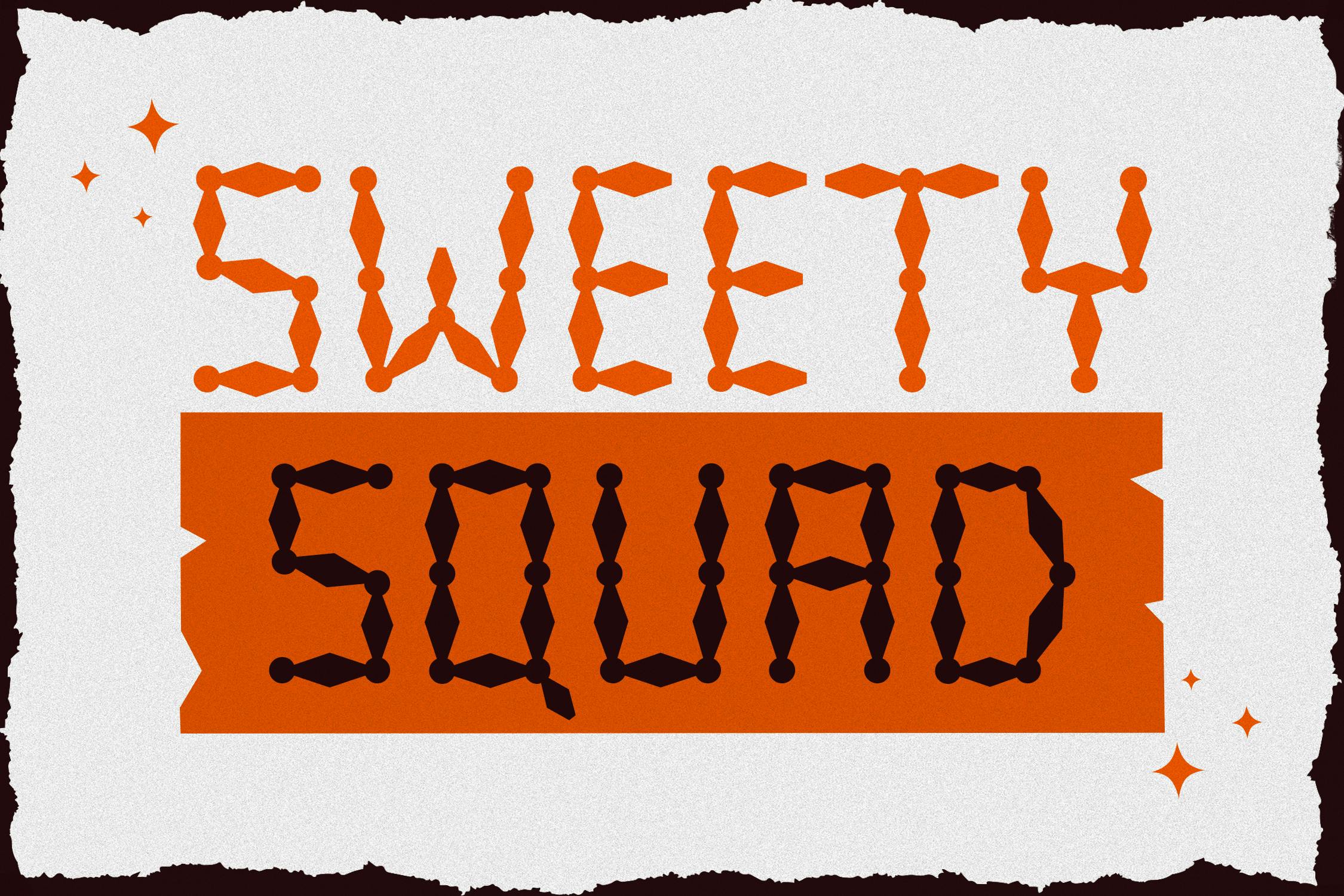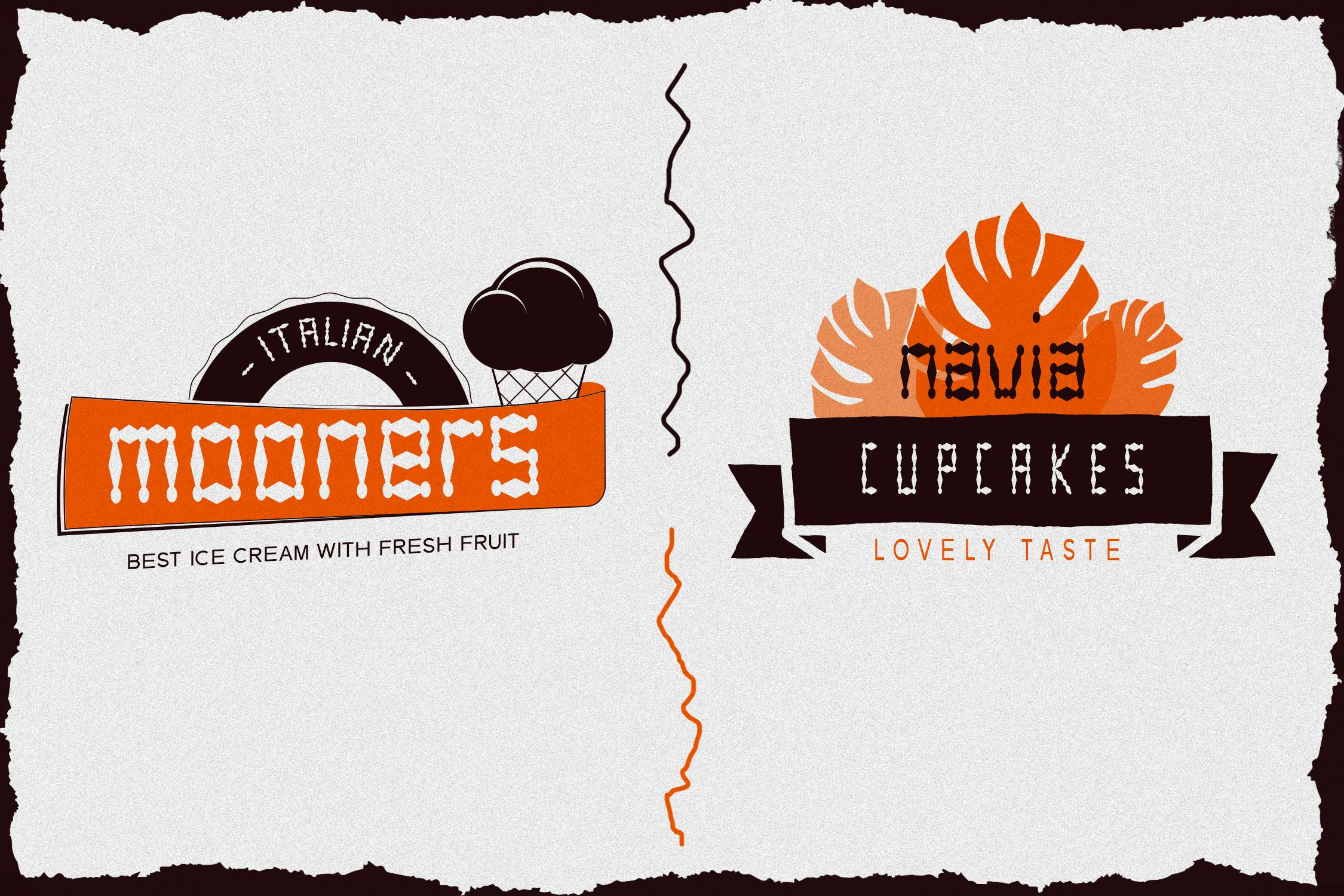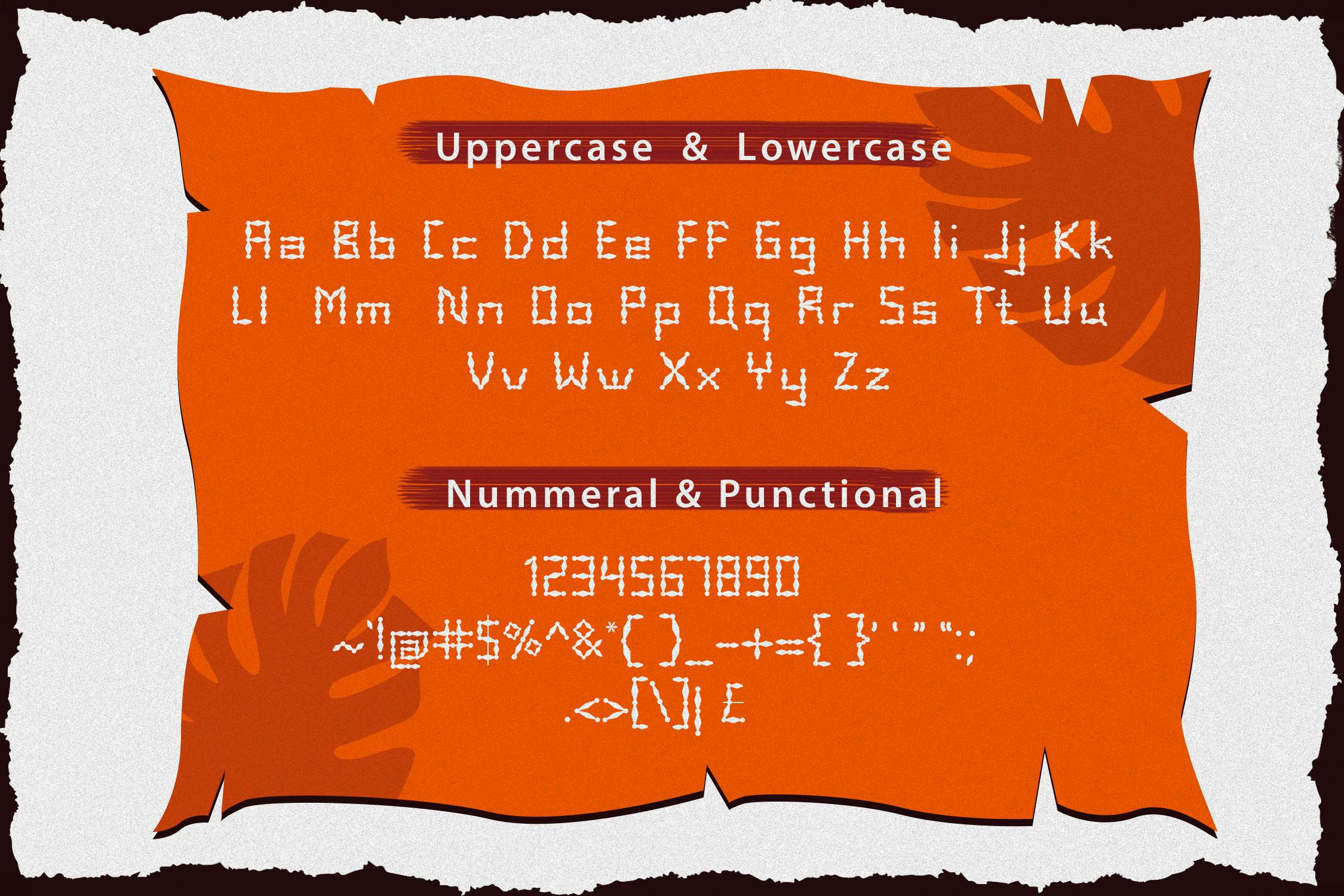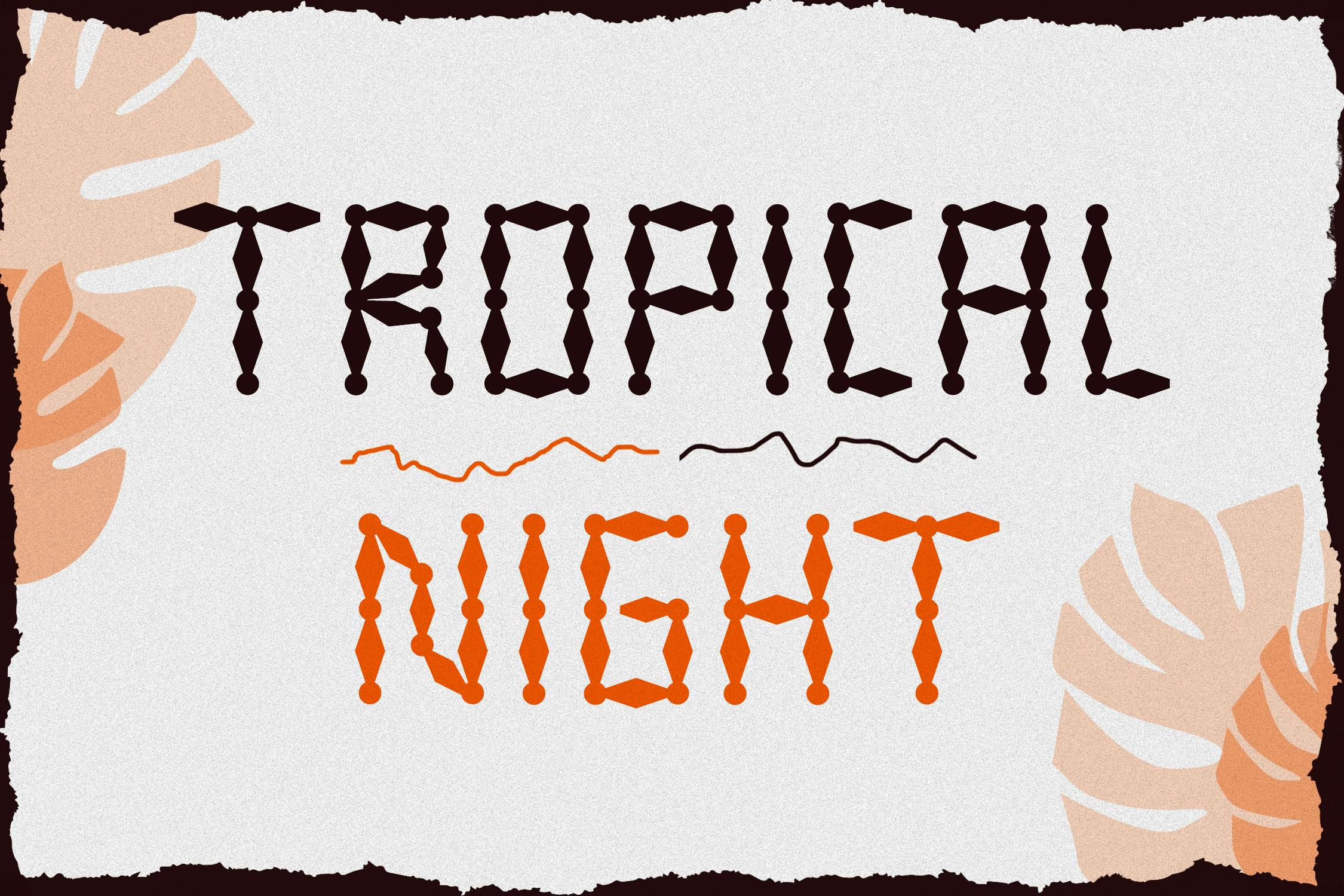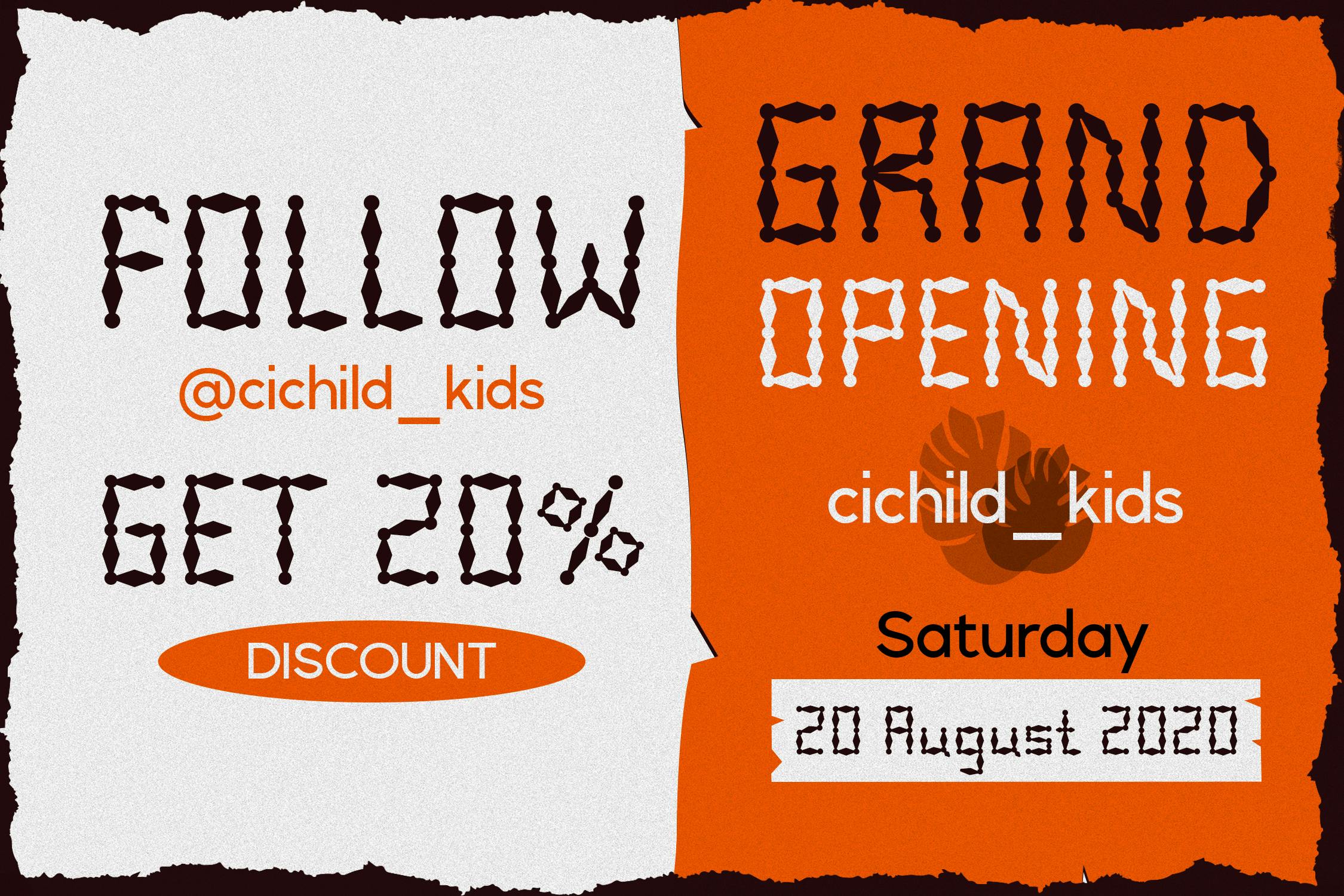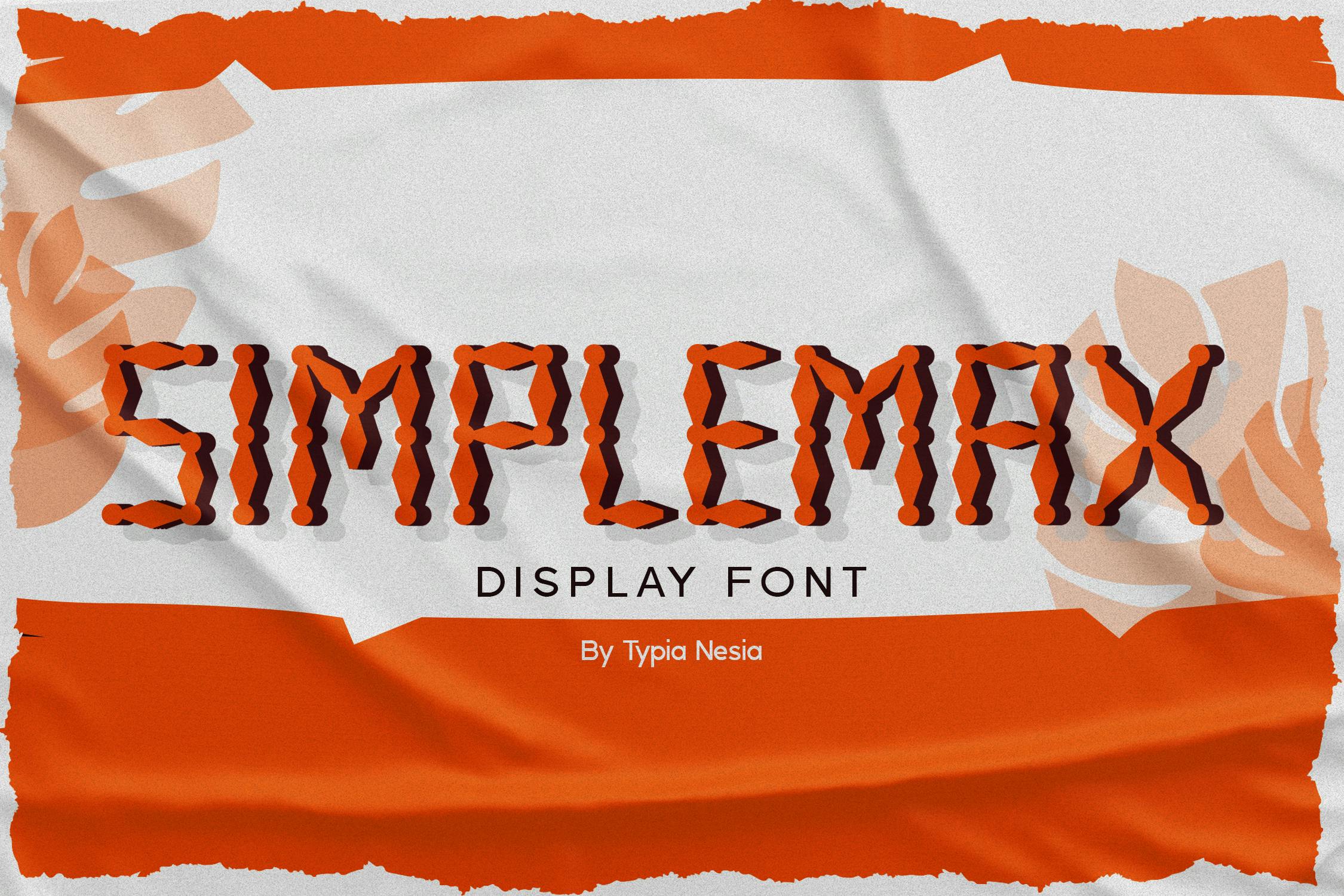
فونت Simplemax - فونت دستساز خلاقانه
فونت Simplemax برای پروژههای آینده شما ایدهآل است. این فونت مناسب برای طراحی لوگو، طراحی نشریات، طراحی لوازمالتحریر، طراحی وبلاگ، طراحی تبلیغات مدرن، دعوتنامهها، نقلقولهای هنری، دکوراسیون منزل، عنوان کتاب/جلد، رویدادهای خاص (مثل تولد و غیره) و بسیاری موارد دیگر میباشد.